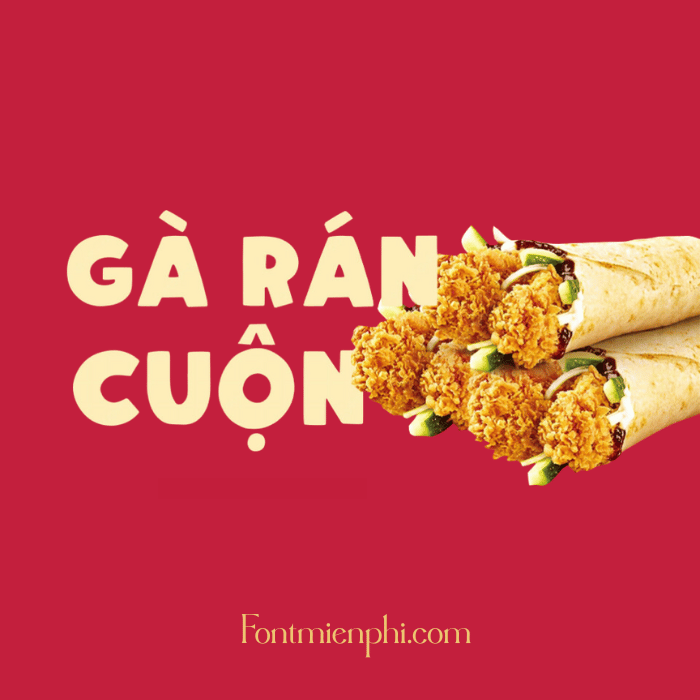
Font Việt hóa 1FTV VIP Hamberger là font chữ Việt hóa cho các thiết kế ẩm thực.
Font Việt hóa 1FTV VIP Hamberger – Phong Cách Độc Đáo, Thiết Kế Chuyên Nghiệp
Font Việt hóa 1FTV VIP Hamberger là bộ font chữ nghệ thuật độc đáo, được thiết kế dành riêng cho dân thiết kế, sáng tạo nội dung. Với nét chữ mềm mại, phá cách nhưng vẫn giữ được sự tinh tế, font chữ này phù hợp cho các dự án poster, logo, banner, hoặc thiết kế đồ họa đầy cá tính.
✔ Nét chữ độc đáo – Phong cách trẻ trung, sáng tạo.
Với font chữ tiếng Việt Hamberger sẽ giúp thiết kế của bạn đẹp hơn, sang trọng hơn. Font Hamberger có nét đậm, dày, bo tròn rất dễ thương nhé. Hi vong font ẩm thực Hamberger sẽ là một font chữ luôn nằm trong bộ sưu tập ưu chuộng của bạn